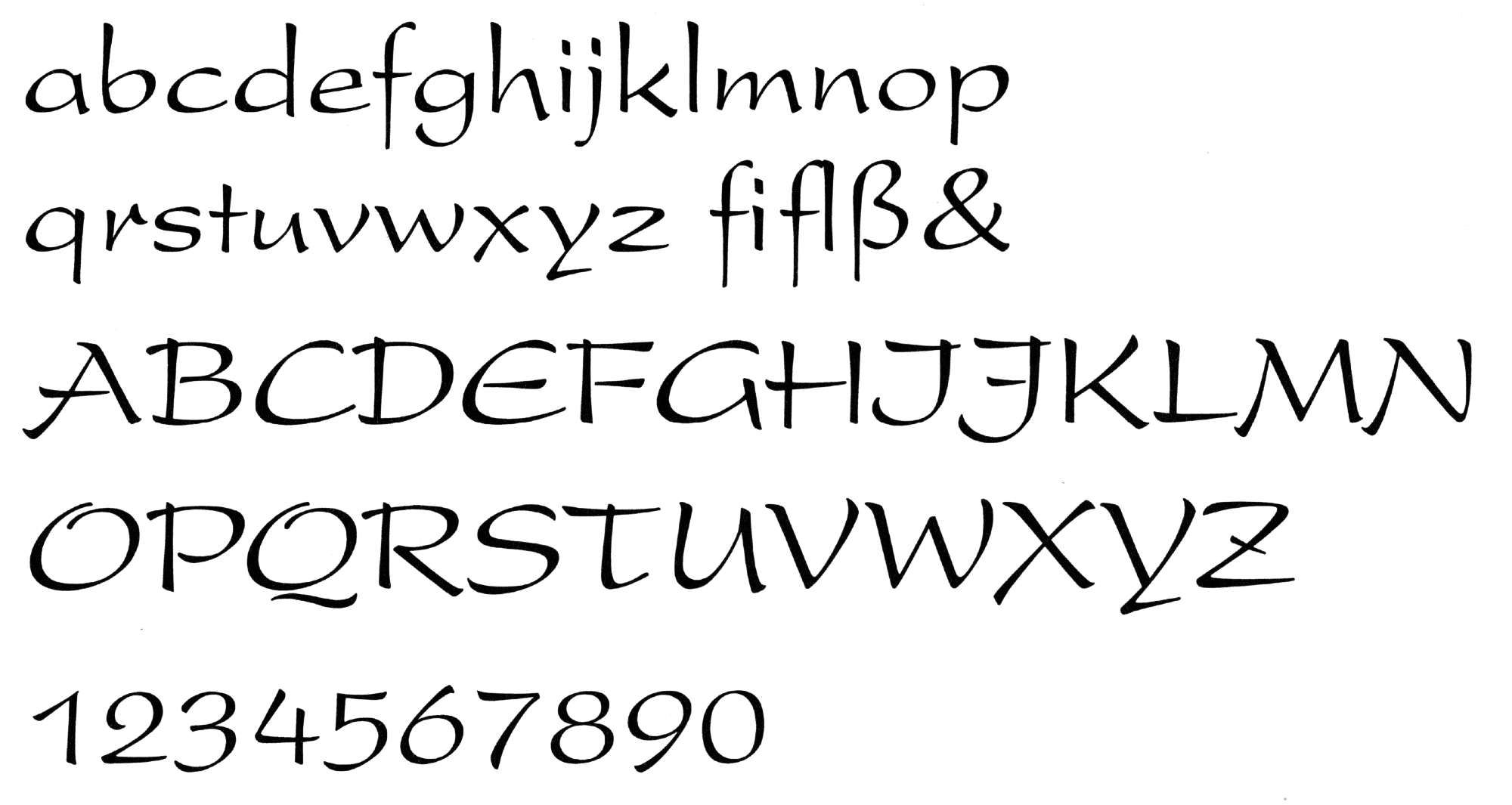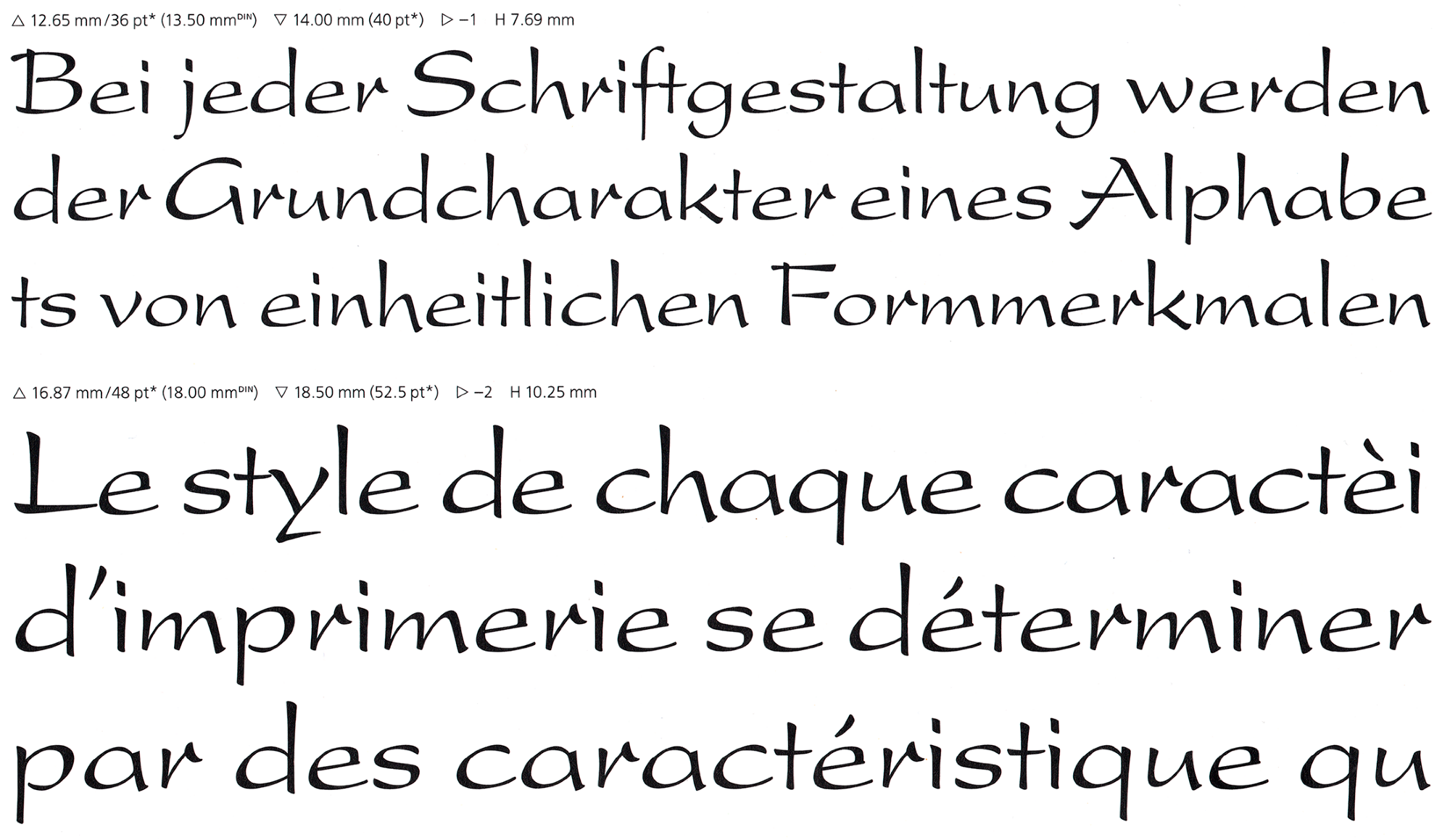
- 1974
- Antiqua dekorativ
Die Present von Friedrich Karl Sallwey erschien 1974 als letzte Handsatz-Schrift bei der D. Stempel AG. Die Schrift besitzt einen beschwingten Pinselduktus, der insbesondere bei den Versalien an asiatische Kalligrafie erinnert. Die Popularität der Schrift führte später zu einem – für eine dekorative Pinselschrift – recht umfangreichen Ausbau in drei Strichstärken und zwei Weiten, die heute über Linotype erhältlich sind.